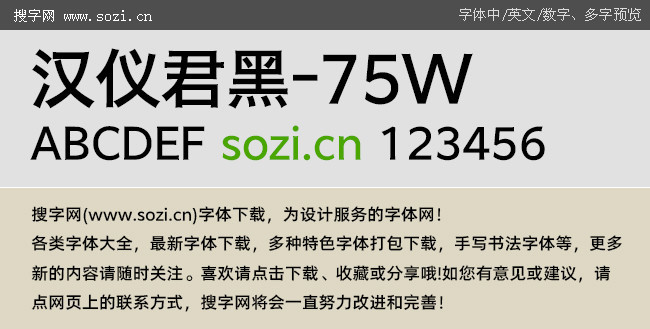
漢儀君黑-75W
搜字網(wǎng)給大家提供一款漢儀君黑-75W中文字體下載,漢儀君黑-75W字體是一款擁有喇叭口的字體,漢儀君黑字體的筆畫(huà)設(shè)計(jì)在傳統(tǒng)黑體的基礎(chǔ)上,控制了起筆收筆的“喇叭口”張度,使其逐漸向現(xiàn)代黑體發(fā)展,更加適合正文排版使用,提高了用戶(hù)的閱讀體驗(yàn)。與現(xiàn)代黑體對(duì)比來(lái)看,漢儀君黑的曲線感增強(qiáng),筆意舒展,細(xì)節(jié)融入了更多人文氣息,優(yōu)雅且更具親和力。與傳統(tǒng)黑體比較而言,漢儀君黑字形略扁,黑白空間比例飽滿(mǎn)且適宜閱讀,讓字體在更小的空間內(nèi)得以清晰展示。(本字體為個(gè)人非商用版,如需要商用請(qǐng)聯(lián)系漢儀公司購(gòu)買(mǎi)版權(quán))